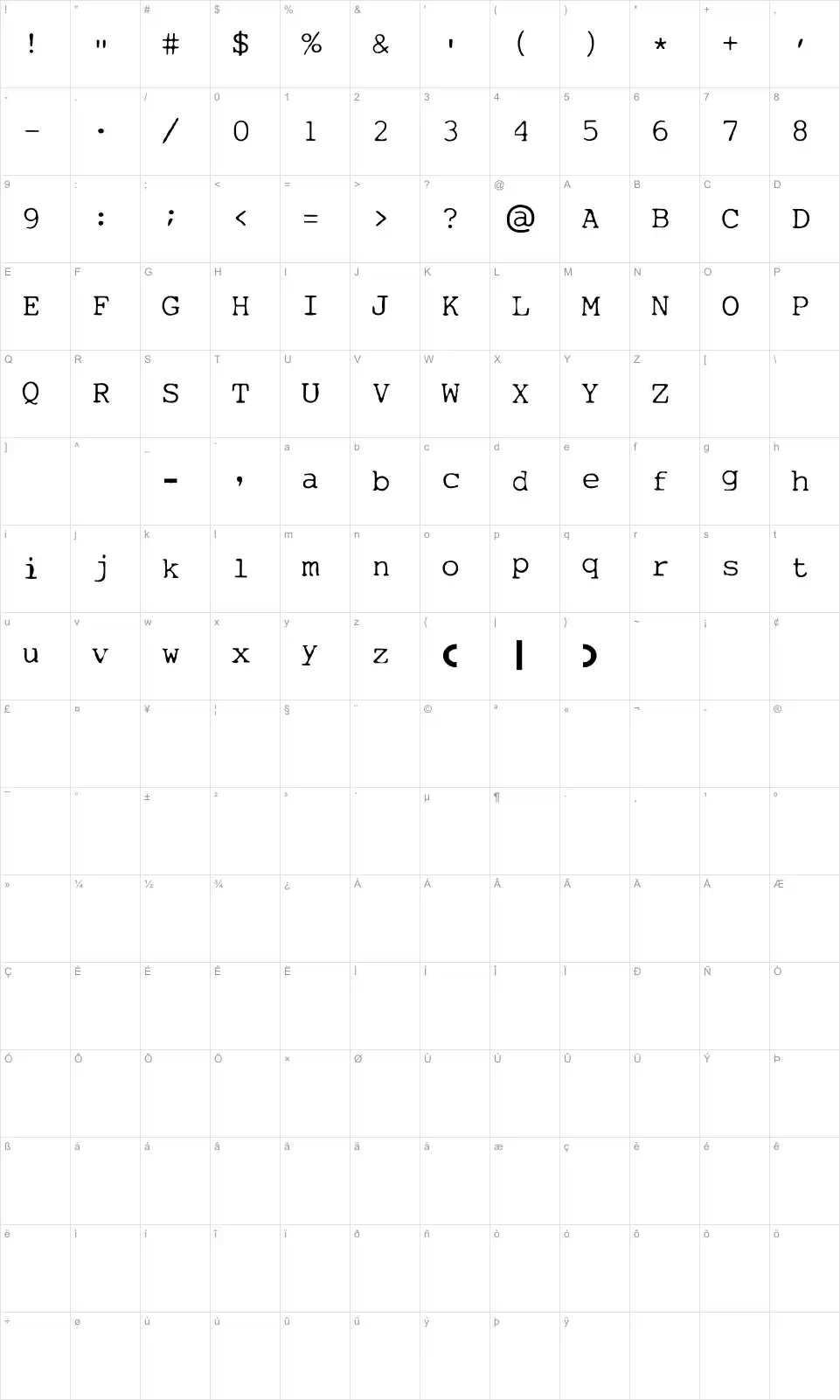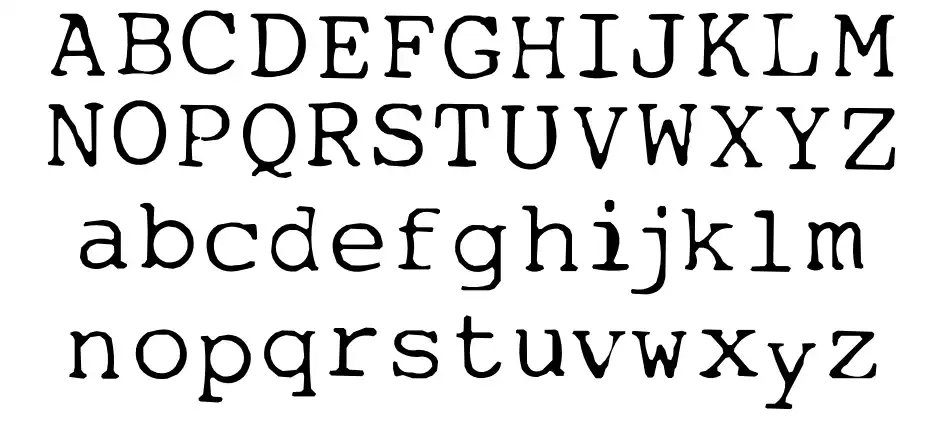
My type of font
Sobre a fonte ‘My Type of Font’, criada pela equipe do 1001 Free Fonts, esta é uma escolha elegante para aqueles que apreciam um estilo retro e sofisticado. Desenvolvida especialmente para quem busca um charme peculiar nas suas criações digitais, essa fonte pertence à categoria Fancy e adota um estilo tipográfico tipicamente vintage, com traços finos e elegantes. A vantagem de usar esta fonte, além do seu estilo único, é que você pode baixá-la diretamente ou gerar um preview de texto personalizado online para verificar como ela se assemelha antes de integrá-la em suas propostas digitais. A fonte está disponível em formato TTF, é totalmente gratuita e tem um tamanho de apenas 10 KB, o que a torna uma opção extremamente conveniente para quem deseja incorporar um toque especial sem comprometer o tempo ou o espaço de armazenamento. Com mais de 10.000 downloads desde sua incorporação em 2022, é evidente que muitos usuários encontraram o estilo e a facilidade desta fonte fascinantes. Visite o site do designer, 1001FreeFonts.com, para explorar uma ampla gama de outras opções criativas e de alta qualidade.
Categoria: Fancy › Typewriter